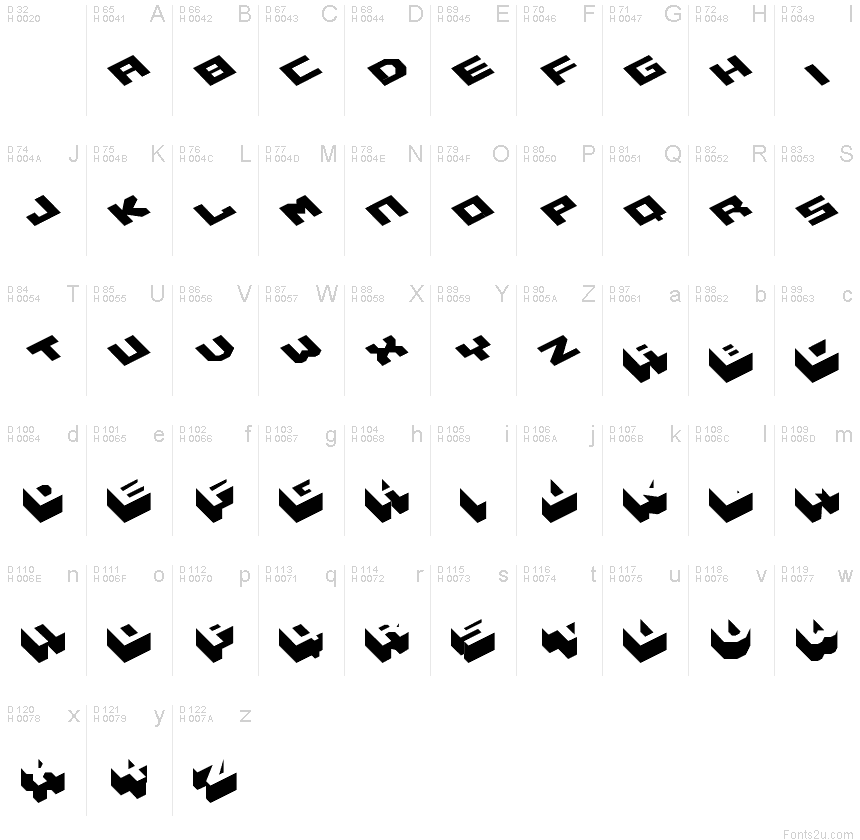
Hexagon od 2theLEFT typefaces to darmowy, trójwymiarowy font typu display, który zamienia każde słowo w masywną, izometryczną strukturę. Każda litera wygląda jak solidny blok wycięty z jednego kawałka, z ostrymi kątami i fasetowanymi krawędziami, które chwytają światło. Wyraziste sylwetki i zwarta geometria nadają mu zabawkowej, futurystycznej energii – tak, jakby Twój tekst został ułożony z lśniących, czarnych klocków.
Dzięki Hexagon nagłówki nie tylko widnieją na stronie – one wysuwają się na pierwszy plan, piętrzą i wydają się niemal namacalne. Ten darmowy font świetnie sprawdza się w tytułach gier, plakatach sci-fi, brandingu wydarzeń technologicznych, opakowaniach zabawek, okładkach muzycznych czy eksperymentalnych logotypach. Aby zachować równowagę, połącz Hexagon z prostym, lekkim krojem bezszeryfowym w tekście głównym i stosuj go w dużym rozmiarze, aby trójwymiarowa głębia i kanciasty rytm pozostały wyraźne i czytelne.
Hexagon